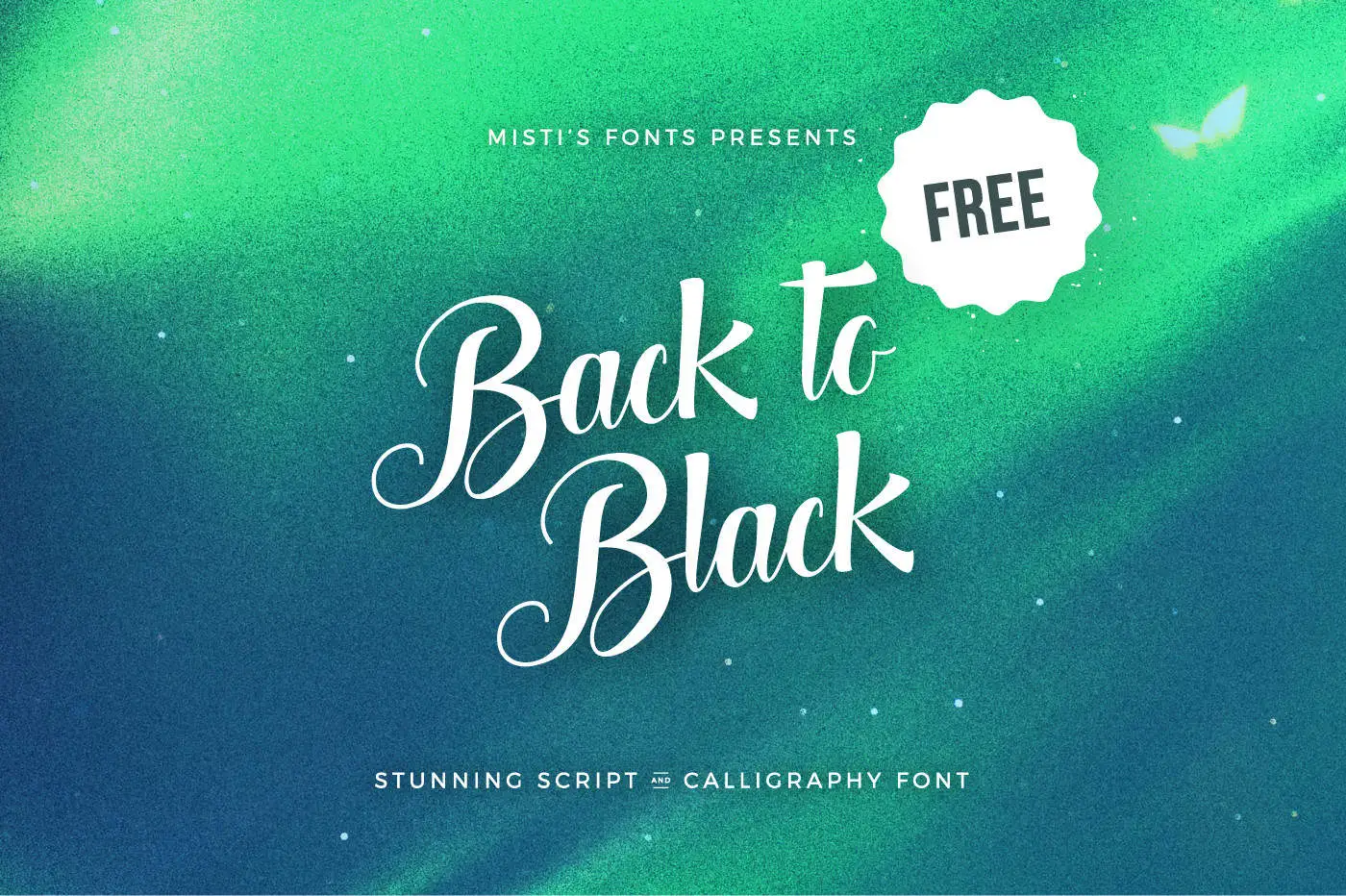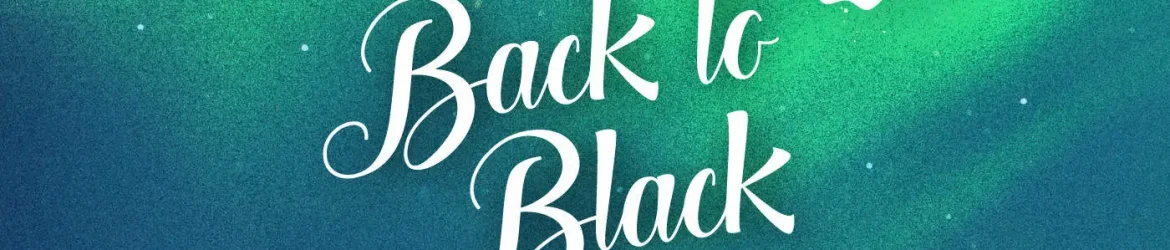
Back to Black Font – Download Grátis
Esta font ‘Back to Black’ é uma verdadeira maravilha para artistas digitais e designers que valorizam a escrita ao estilo do xadrez. Misti’s Fonts apresentou essa belíssima fonte de chamada há algum tempo, mas recentemente atualizaram suas imagens presentes e incluíram informações sobre o criador em seu site oficial. Esta é uma font exclusiva, destinada a ser escrita por qualquer usuário para fins pessoais ou benfeitorias sociais. Eu tentei usar essa font na minha própria criação e senti que ela me proporcionou um senso de satisfação e beleza sem precedentes. Agora, se você precisa incorporar essa maravilhosa fonte em um projeto comercial, Misti’s Fonts está disponível para auxiliar. Se estiver interessado em adquirir uma licença comercial, é só entrar em contato com o criador para mais detalhes e disponibilidade. A font ‘Back to Black’ não apenas é linda a olho nu, mas também oferece um nível de sofisticação e elegância que qualquer designer pode valorizar em seus trabalhos.